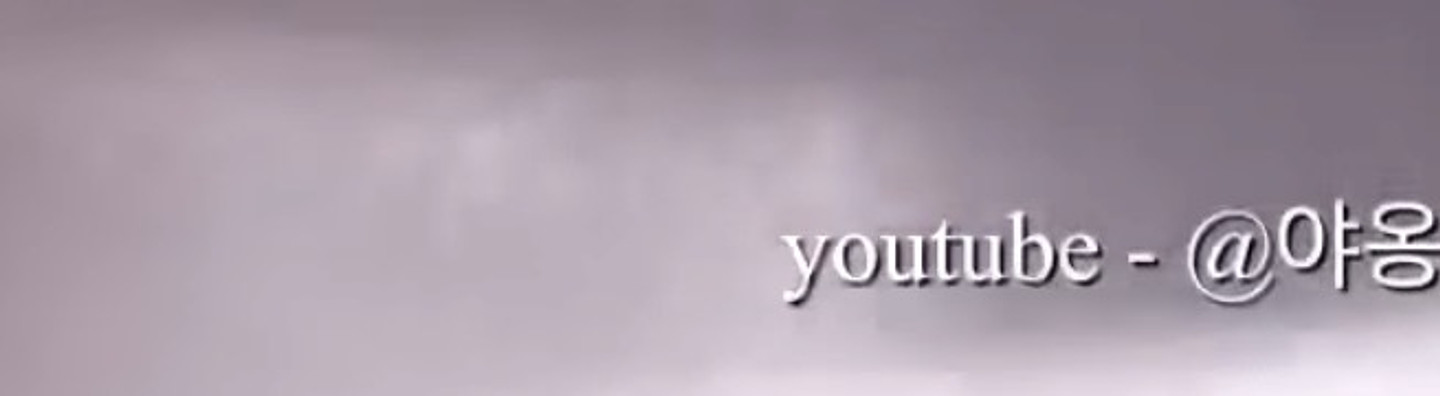
이 폰트가 어떤건지 궁금해여 ㅠㅠ
폰트 찾을 수 있을까요? 그냥 인터넷에서 주운 이미지인데.. 괄호가 완전 둥그스름 형태가 아니고 살짝 각이 있는 특징이 있습니다 ㅠㅠ
혹시 어떤 폰트인지 아실까요?ㅠㅠㅠ
이거 무슨 폰트인지 아시는분 계신가요?ㅠㅠ 미리 감사합니다 ㅠㅠ
이거 무슨 폰트 인가요?! 프리텐다드와 노토산스는 아닙니다ㅜ